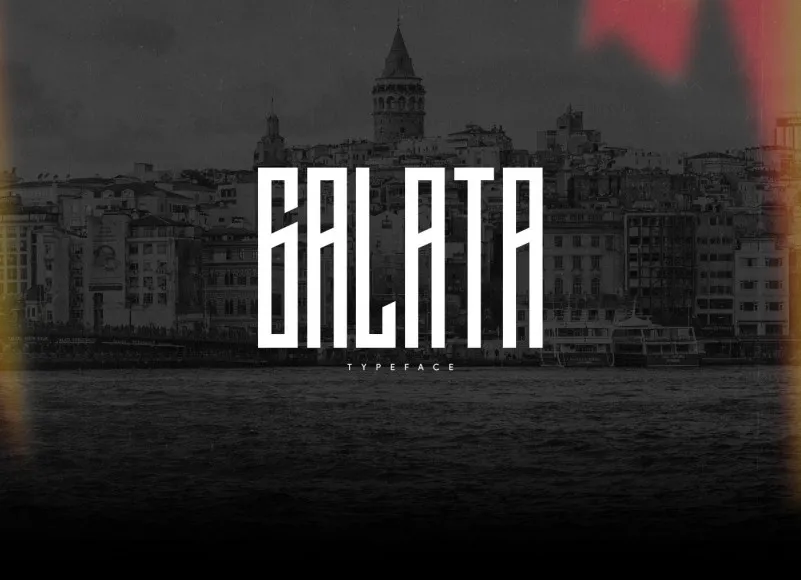
Galata Font – Download Grátis
A Galata Font é uma escolha excepcional para quem busca uma fonte de exibição que destaque seus projetos visuais com estilo e elegância. Desenvolvida cuidadosamente, ela aposta na harmonia das formas do texto e eleva a altura dos ascenderes, criando um equilíbrio visual que torna o design único e autêntico. Seu formato condensado faz dela uma opção perfeita para aplicar em designs como estandartes de rua, logotipos, panfletos e muito mais. Esta fonte é ideal não apenas por sua aparência impecável, mas também pela facilidade com que ela se adaptará aos diferentes formatos de texto. A Galata Font é perfeita para aqueles que desejam destacar seu design em espaços de grande visibilidade, como outdoors e logotipos em publicações. A qualidade desta fonte a torna uma escolha segura e confiável para designers propondo ambientes digitais ou físicos que precisem ser percebidos do primeiro olhar.